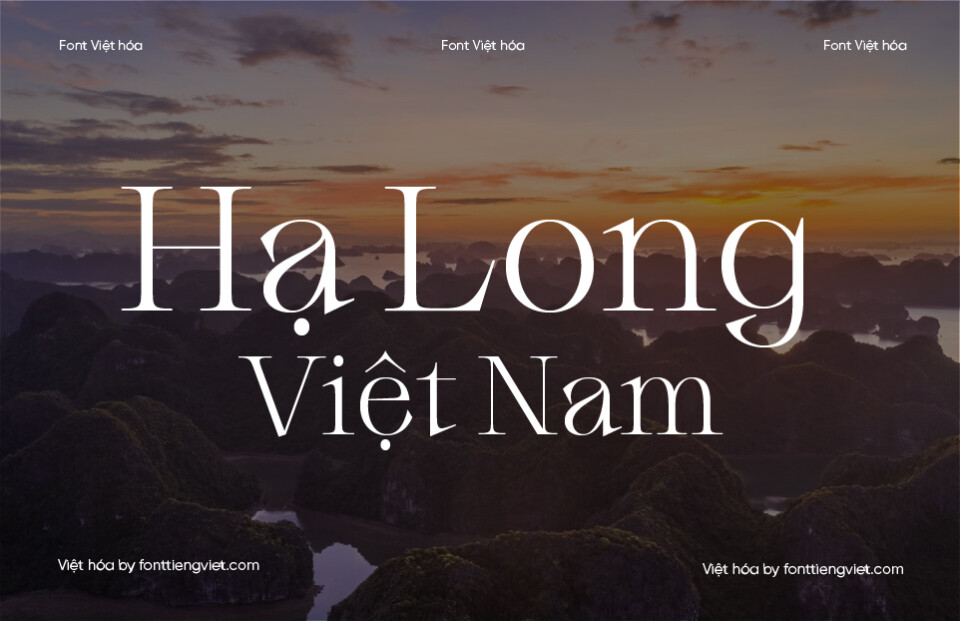
Font Việt hóa 1FTV VIP Decay White Std
Trong thế giới đồ họa hiện đại, việc lựa chọn một bộ Font Việt hóa 1FTV VIP Decay White Std chất lượng đóng vai trò then chốt giúp sản phẩm của bạn trở nên nổi bật và chuyên nghiệp hơn. Đối với các bạn học sinh và giáo viên, việc tiếp cận những bộ Font Miễn Phí không chỉ giúp tiết kiệm chi phí mà còn mở ra không gian sáng tạo vô tận cho các bài thuyết trình hay báo tường. Bộ phông chữ này được đội ngũ 1FTV tinh chỉnh kỹ lưỡng, đảm bảo tính thẩm mỹ cao và sự ổn định tuyệt đối khi gõ tiếng Việt trên các phần mềm thiết kế phổ biến hiện nay.
Đặc điểm nổi bật của Font Việt hóa 1FTV VIP Decay White Std
Phong cách thiết kế độc đáo và hiện đại
Bộ Font Việt hóa 1FTV VIP Decay White Std mang trong mình sự kết hợp hoàn hảo giữa nét cổ điển và hơi thở đương đại. Các đường nét được gọt giũa tỉ mỉ, tạo nên cảm giác thanh thoát nhưng vẫn vô cùng mạnh mẽ. Điểm đặc trưng của dòng “Decay” chính là sự phá cách trong cấu trúc chữ, giúp thông điệp của bạn dễ dàng thu hút ánh nhìn từ lần đầu tiên. Đây là lựa chọn lý tưởng cho những ai muốn tìm kiếm sự khác biệt trong các dự án thiết kế logo, poster hoặc bìa sách học thuật.
Tối ưu hóa khả năng hiển thị tiếng Việt
Một trong những rào cản lớn nhất khi sử dụng phông chữ ngoại quốc là lỗi dấu tiếng Việt. Tuy nhiên, với phiên bản Font Việt hóa 1FTV VIP Decay White Std, mọi ký tự đặc biệt đều đã được xử lý hoàn tất. Các dấu thanh như huyền, sắc, hỏi, ngã, nặng được đặt ở vị trí cân đối, không bị chồng chéo hay quá nhỏ, giúp văn bản duy trì được sự mạch lạc và dễ đọc ngay cả ở kích thước nhỏ nhất.
Ứng dụng thực tế trong học tập và giảng dạy
Sáng tạo bài giảng điện tử sinh động
Các thầy cô giáo có thể sử dụng Font Việt hóa 1FTV VIP Decay White Std để làm tiêu đề cho các slide bài giảng PowerPoint. Sự mới lạ của phông chữ này sẽ giúp học sinh tập trung hơn vào nội dung chính, từ đó nâng cao hiệu quả truyền đạt kiến thức. Trong môi trường sư phạm, việc thay đổi những phông chữ mặc định nhàm chán bằng một bộ phông chữ có cá tính sẽ tạo ra nguồn cảm hứng học tập mới mẻ cho các em học sinh mỗi ngày đến trường.
Thiết kế ấn phẩm truyền thông trường học
Đối với các bạn học sinh tham gia câu lạc bộ hoặc ban truyền thông, Font Việt hóa 1FTV VIP Decay White Std là công cụ đắc lực để thiết kế avatar, banner cho các sự kiện văn nghệ hay giải đấu thể thao. Tính ứng dụng cao của bộ font này cho phép nó xuất hiện từ những tấm thiệp mời trang trọng đến những tờ rơi thông báo năng động, giúp hình ảnh của nhà trường luôn chuyên nghiệp trong mắt phụ huynh và cộng đồng.
Kết luận về bộ phông chữ 1FTV VIP Decay White Std
Việc sở hữu bộ Font Việt hóa 1FTV VIP Decay White Std trong kho tài nguyên thiết kế sẽ giúp bạn tự tin hơn khi thực hiện các dự án sáng tạo của mình. Với ưu điểm là phông chữ hoàn toàn tương thích tiếng Việt và có tính thẩm mỹ vượt trội, đây thực sự là món quà ý nghĩa dành cho cộng đồng yêu cái đẹp. Hãy cùng trải nghiệm và lan tỏa tinh thần học tập sáng tạo bằng cách tải ngay Font Miễn Phí, Font Việt Hóa, Font Việt hóa 1FTV VIP Decay White Std để bắt đầu hành trình biến những ý tưởng trên giấy thành những tác phẩm nghệ thuật thực thụ ngay hôm nay.